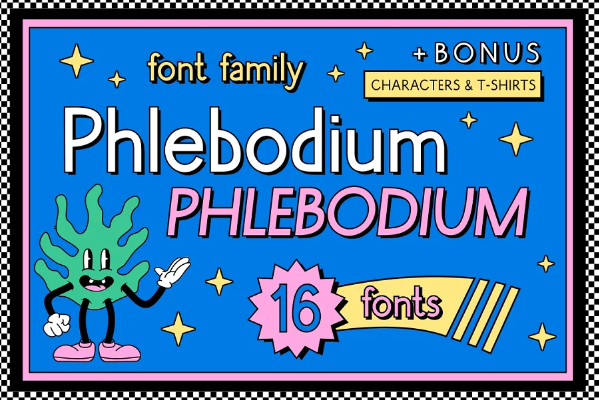
Phlebodium - геометрический шрифт sans serif, 16 шрифтов
Phlebodium - современный геометрический шрифт без засечек. Ностальгический, мягкий и игривый шрифт в стиле техно-рейв 80-х 90-х 2000-х годов. БОНУС: векторные конопляный / конопляный лист, подсолнух, гриб / грибок, мясо, единорог, сердце, пицца, хот-дог, солнце, флебодиум, клевер, собака, кошка, медведь, солнце персонаж талисман иллюстрации и дизайны футболок
Этот смелый шрифт идеально подходит для использования в размерах дисплея. Идеально подходит для заголовков и логотипов, текстовых блоков, любого вида графического дизайна, печати, футболок, плакатов, брендинга, веб-приложений, социальных сетей и многого другого.
Шрифт Phlebodium содержит 4 веса, нормальный, конденсированный и курсивный стили.